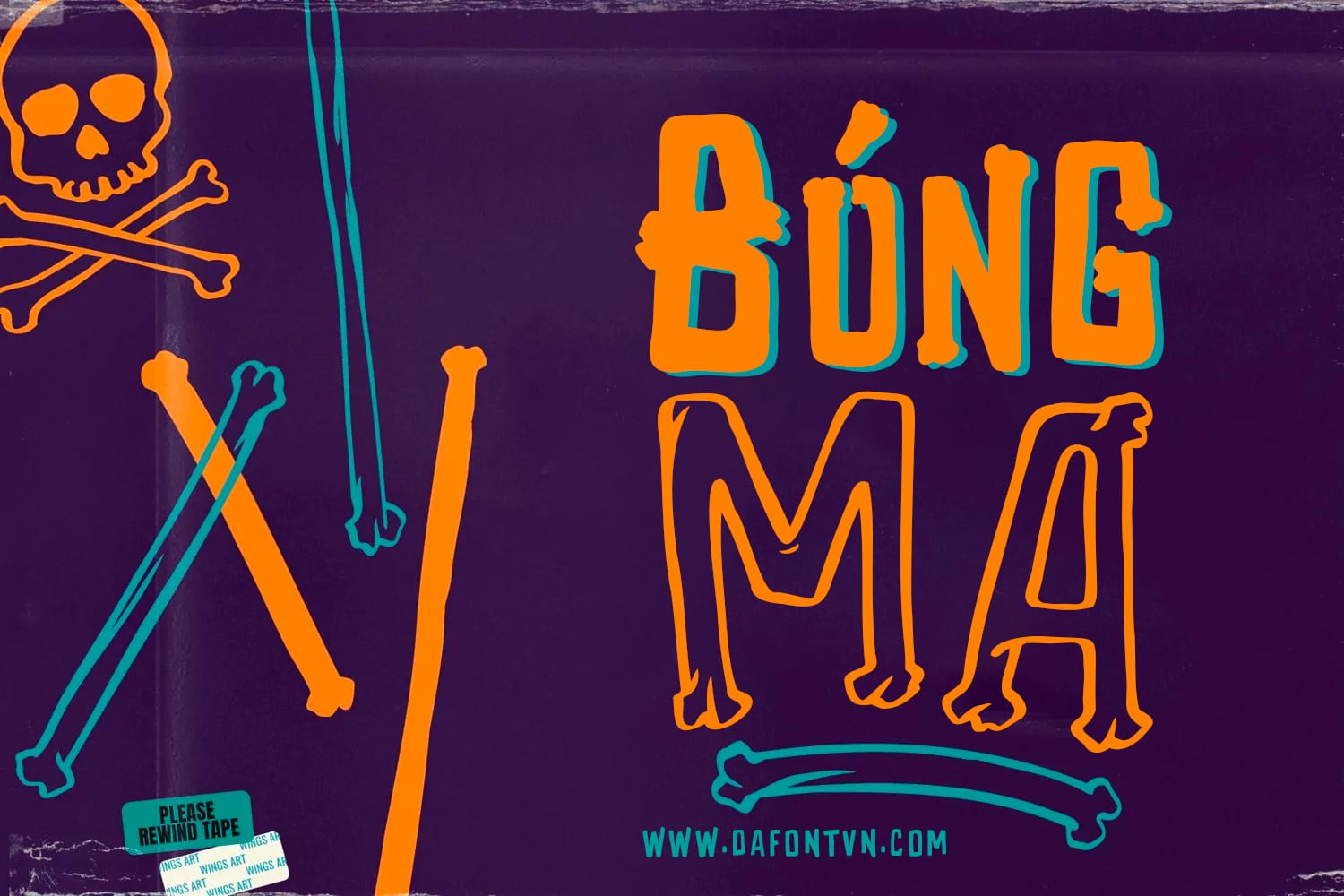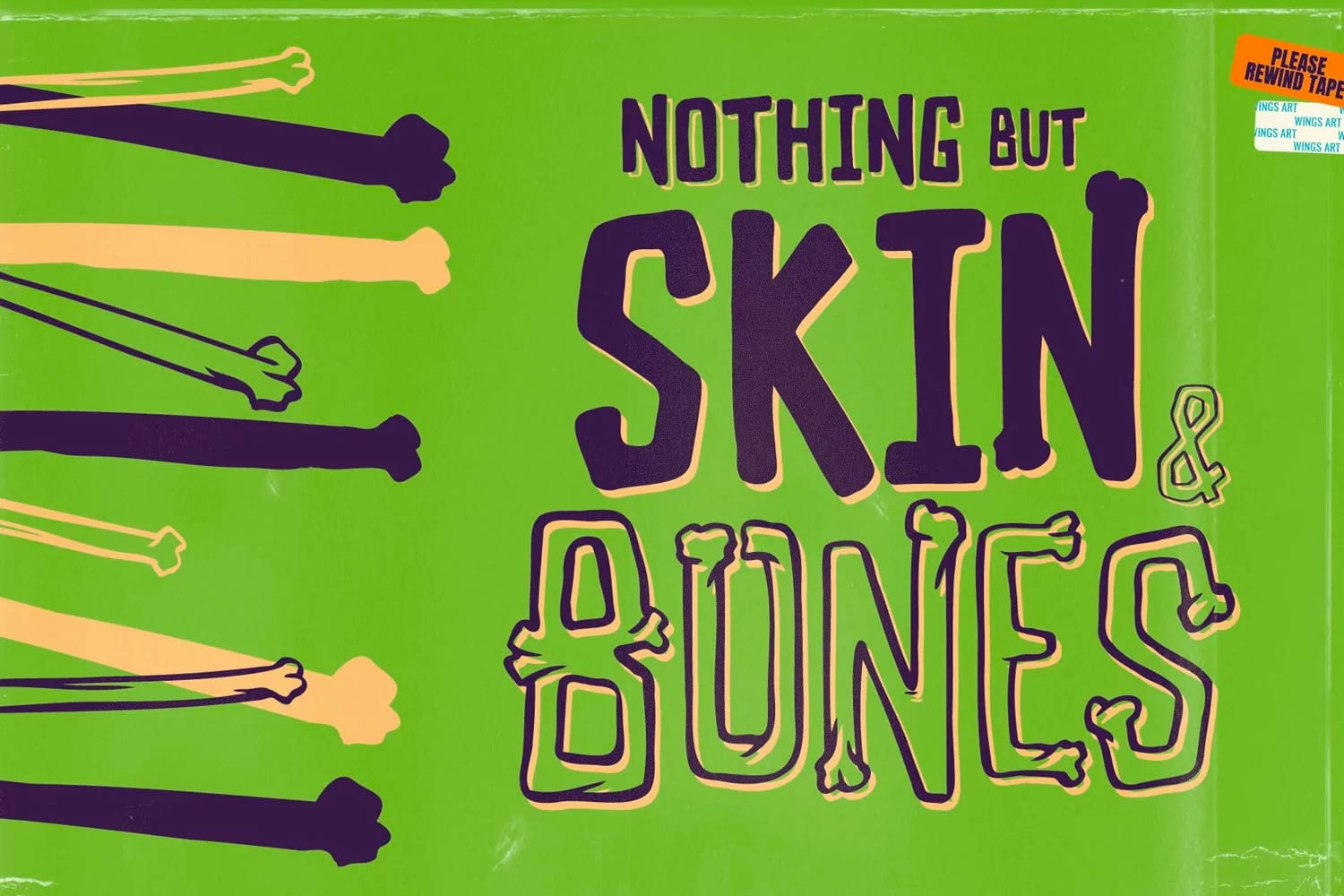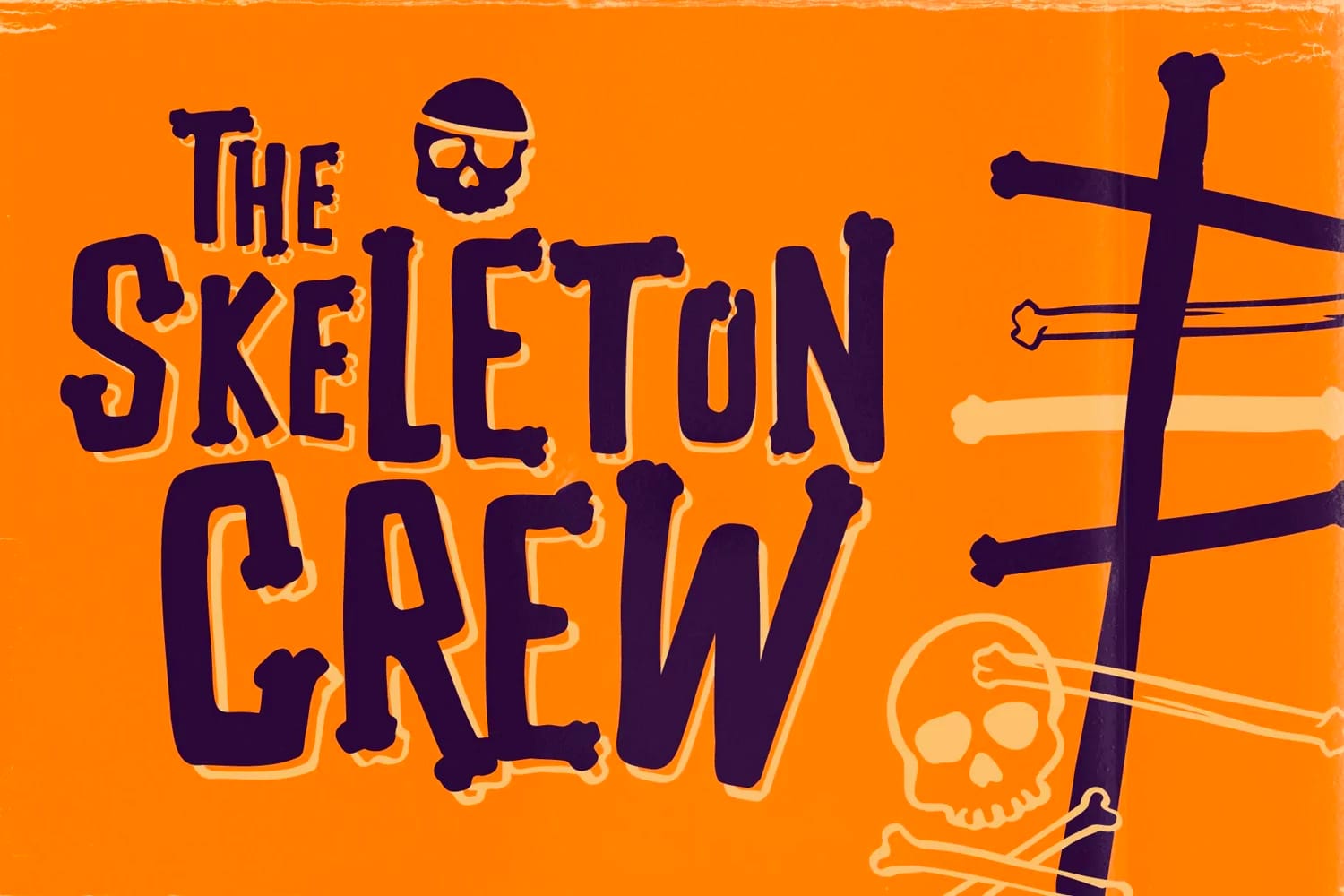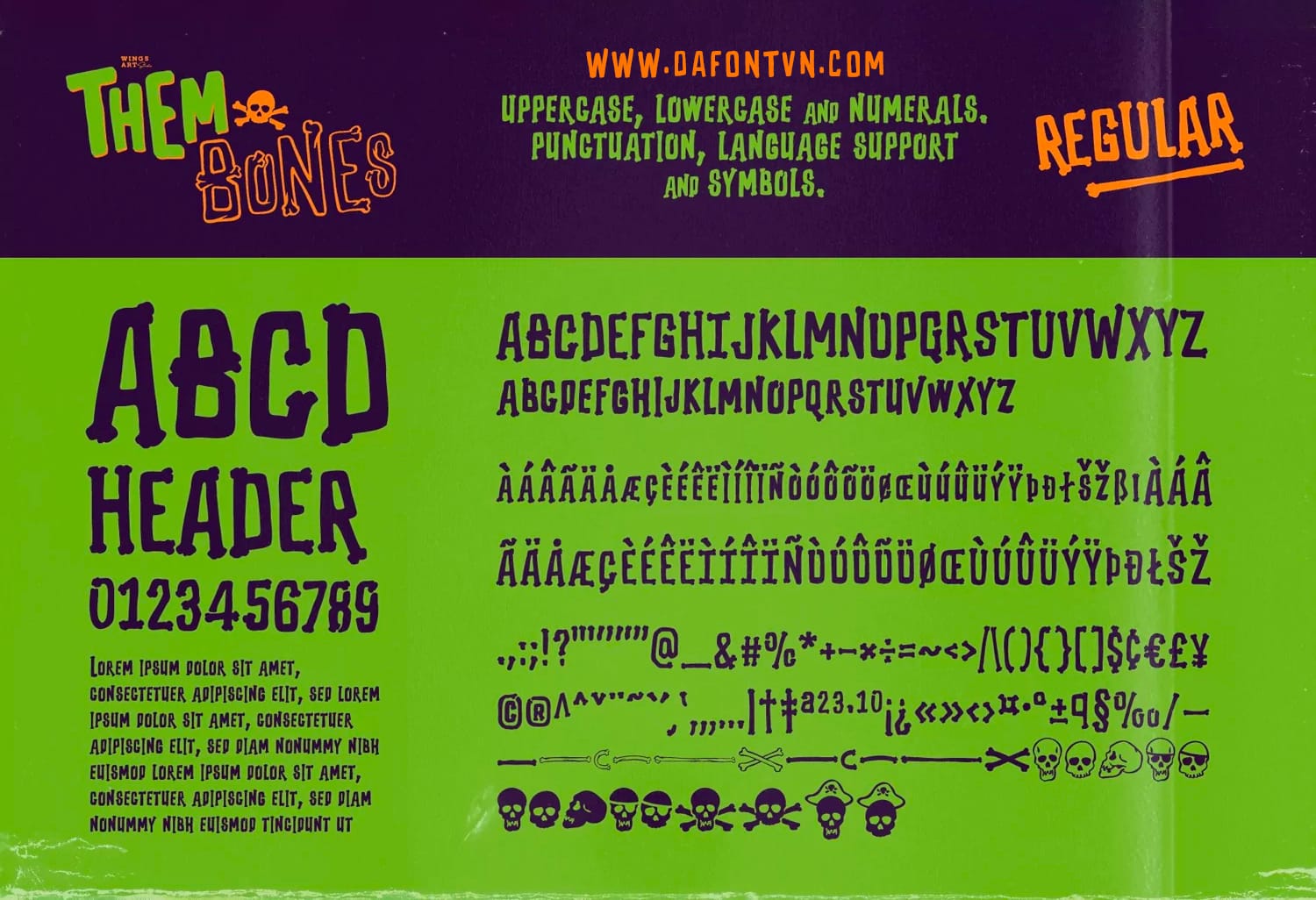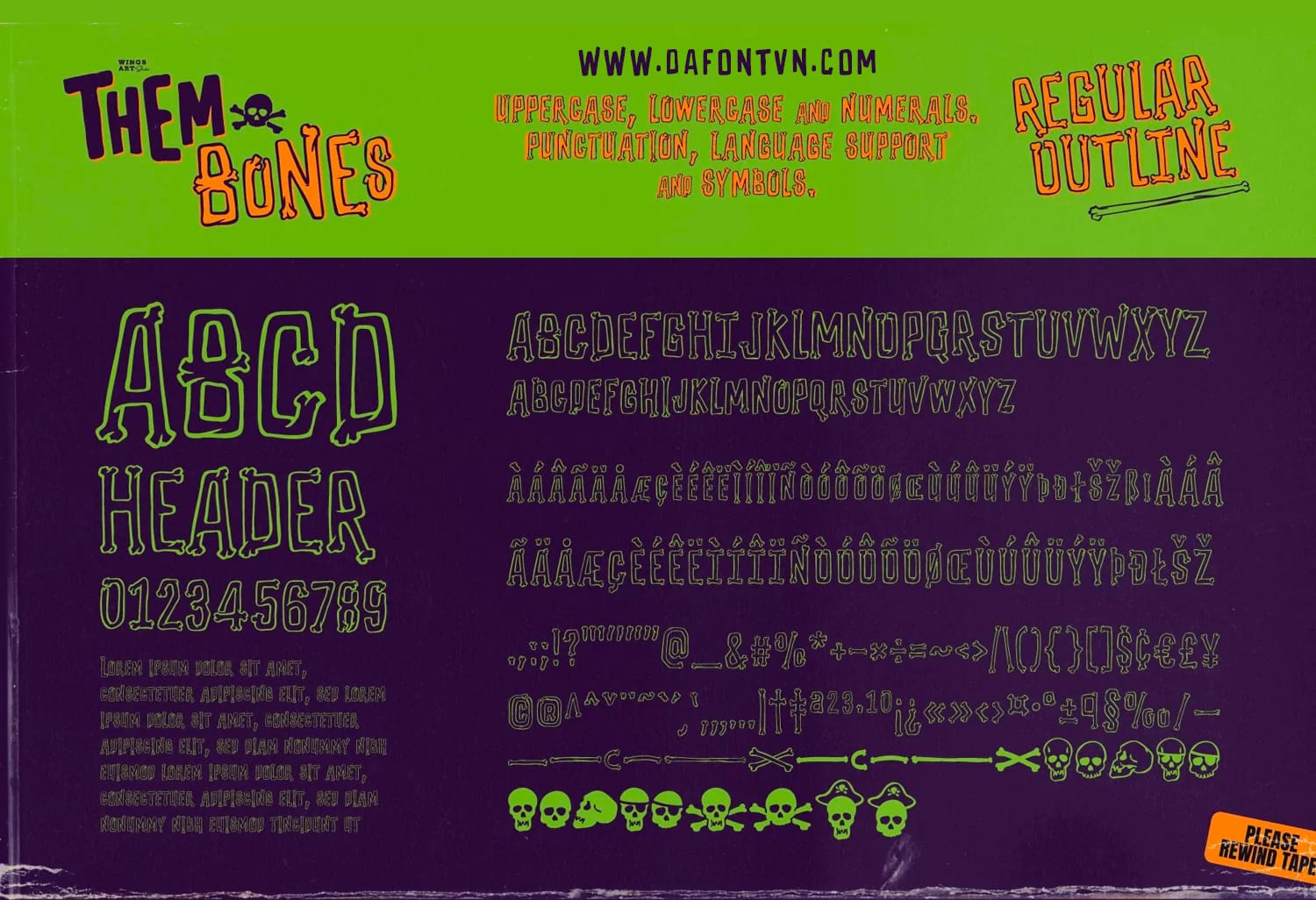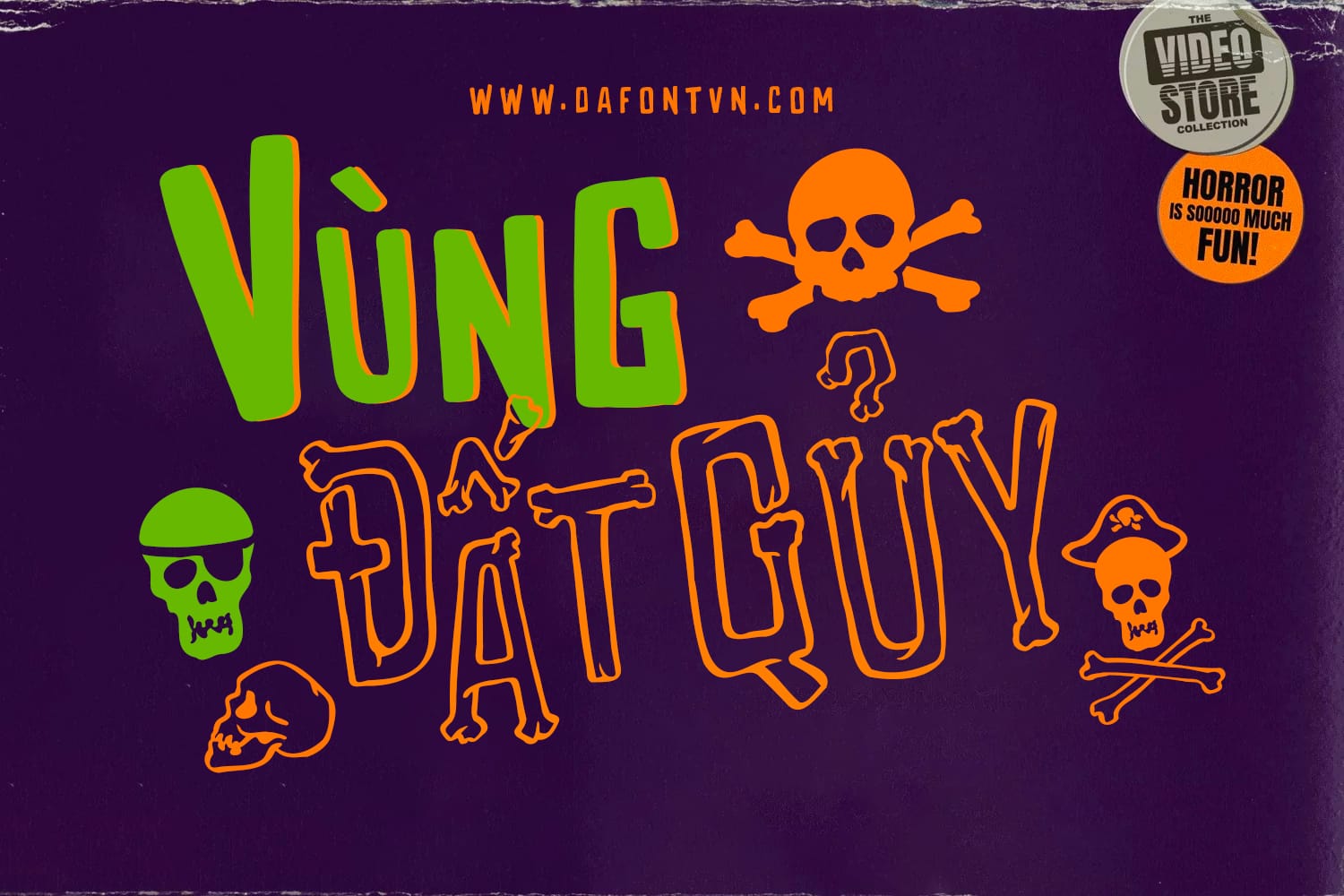
Them Bones Font là một phông chữ được vẽ tay mang phong cách Halloween được lấy cảm hứng từ những bộ xương cổ đại và những con tàu cướp biển ma quái. Nó có thiết kế vui nhộn, nhẹ nhàng không kém phần rùng rợn vì vậy khá phù hợp cho các thiết kế Halloween, phim truyện, poster…
Phông chữ có viết hoa và viết thường, với phông chữ viết hoa có một thiết kế mới lại được vẽ thủ công trông giống như những chiếc xương cũ và một sự thay thế linh hoạt.
Them Bones được việt hóa đầy đủ 5 kiểu, kerning, features và được chỉnh sửa lại khá hoàn chỉnh các chữ thường cho phù hợp với các dấu.
Việt hóa đầy đủ 5 kiểu bao gồm:
- Them Bones Regular
- Them Bones Regular Outline
- Them Bones Alternative
- Them Bones Alternative Outline
- Them Bones Underlines